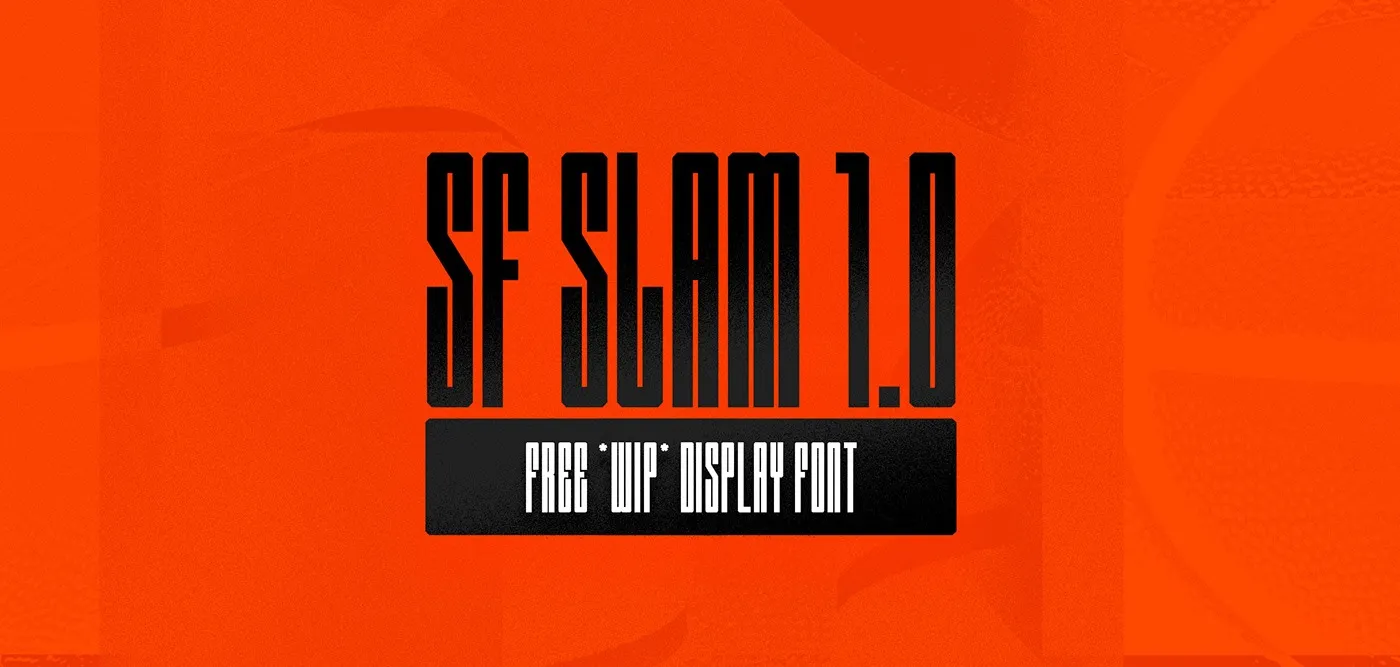
SF SLAM 1.0 Font
Essa font SF SLAM 1.0 é perfeita para aqueles que buscam uma fonte Display vibrante e poderosa. Ela é especialmente adaptada para headlines impactantes, criando um caráter distintivo e emocionante que se destaca em qualquer contexto visual. Fabricada pelo designer STUDIO FRAZER, essa font eleva o impacto de seus títulos largos, garantindo uma presença forte mesmo quando usados em formato minúsculo sem perder a sua força e personalidade. Ideal para logotipos modernos, designs contemporâneos da web ou headlines impressas, ela enriquece qualquer projeto com um toque inovador e atual. Não perca tempo: adquira já essa font poderosa hoje!